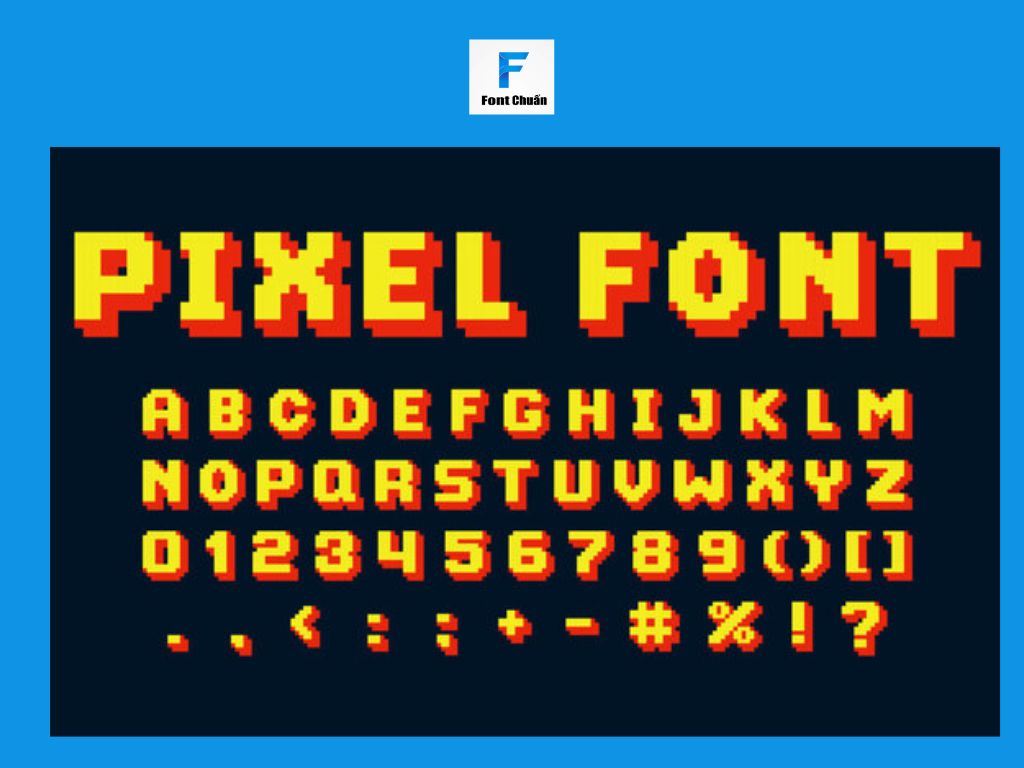
Top font chữ Minecraft Việt hóa HOT nhất | Free download
Bạn là fan của Minecraft và muốn biến mọi thiết kế, banner, poster hay dự án cá nhân trở nên độc đáo hơn với font Minecraft giống trong trò chơi?  Trong bài viết này, chúng tôi tổng hợp 11+ font chữ Minecraft hot nhất, đẹp mắt, dễ sử dụng và đặc biệt là tải xuống hoàn toàn miễn phí.
Font chữ Minecraft là gì?
Font Minecraft là kiểu chữ được thiết kế dựa trên phong cách đặc trưng của trò chơi Minecraft – nổi bật với những khối vuông (blocky), dạng pixel cổ điển và đường nét sắc cạnh. Chính sự vuông vức này tạo cảm giác mạnh mẽ, gọn gàng và gắn liền với thế giới “xây dựng từ khối” đặc trưng của game.
Không chỉ được sử dụng trong giao diện và logo chính thức của Minecraft, font chữ này còn trở thành lựa chọn phổ biến trong nhiều lĩnh vực thiết kế. Nhờ phong cách độc đáo, font Minecraft thường xuất hiện trong poster, banner, thumbnail YouTube, thiết kế game Roblox, đồ họa mạng xã hội hay thậm chí trong các dự án cá nhân mang hơi hướng sáng tạo.
Điểm đặc biệt là font chữ Minecraft không chỉ là 1 trong các loại font chữ kiểu đẹp thực tế mà còn gợi nhớ đến trò chơi đình đám mà còn mang lại cảm giác “retro pixel” gần gũi, thích hợp để tạo dấu ấn cá tính trong thiết kế hiện đại.
11+ font Minecraft phổ biến hiện nay
Font Minecraft không chỉ có một phiên bản duy nhất mà đã được phát triển thành nhiều biến thể khác nhau, phù hợp với nhu cầu thiết kế đa dạng. Dưới đây là những font nổi bật mà người dùng thường lựa chọn.
Font Minecraft nguyên bản
Minecraft Ten
Đây là font chữ Minecraft mặc định đi kèm với game Minecraft, giữ trọn vẹn tinh thần blocky, đơn giản và dễ nhận diện.
MineCrafter
Một trong những font nổi tiếng nhất với khối vuông sắc nét, thường được dùng cho logo hoặc tiêu đề lớn nhờ sự mạnh mẽ, nổi bật.
Minecraft Dungeons Font
Được lấy cảm hứng từ phiên bản Minecraft Dungeons, font này mang hơi hướng phiêu lưu và khác biệt, tạo cảm giác mới mẻ trong thiết kế.
Pixel Minecraft
Kiểu chữ dạng pixel cổ điển, rất thích hợp với những ai yêu thích phong cách retro và muốn gợi nhớ đến thẩm mỹ game 8-bit.
Font chữ Minecraft Việt hóa
Với nhu cầu thiết kế tại Việt Nam, việc Việt hóa font Minecraft trở nên cần thiết để tránh lỗi hiển thị dấu và hỗ trợ gõ tiếng Việt đầy đủ. Điều này giúp font trở nên thực tiễn hơn cho người sáng tạo nội dung và nhà thiết kế.
Một số font Việt hóa được dùng nhiều gồm:
MineCrafter Việt hóa
Giữ nguyên phong cách sắc nét nhưng hỗ trợ đầy đủ dấu tiếng Việt, phù hợp khi làm logo hoặc tiêu đề nổi bật.
Pixel Block Việt hóa
Font dạng pixel hỗ trợ Unicode, rất hợp để làm poster, banner hoặc thumbnail cho kênh YouTube gaming.
Minecraft Việt hóa: SVN-Determination Sans
Giữ nguyên tinh thần nguyên bản của font Minecraft mặc định, nhưng được bổ sung khả năng gõ tiếng Việt mà không bị lỗi font.
Trong Roblox, việc sáng tạo giao diện và trải nghiệm người chơi không chỉ nằm ở gameplay mà còn đến từ yếu tố hình ảnh. Font chữ Minecraft với dạng blocky đặc trưng giúp game thêm phần cá tính, đặc biệt phù hợp với các map mang phong cách sáng tạo, pixel hoặc retro.
• Chọn đúng kích thước chữ: Font Minecraft có dạng pixel, nếu để quá nhỏ sẽ bị vỡ hoặc khó đọc. Nên để size trung bình trở lên để giữ sự rõ ràng.